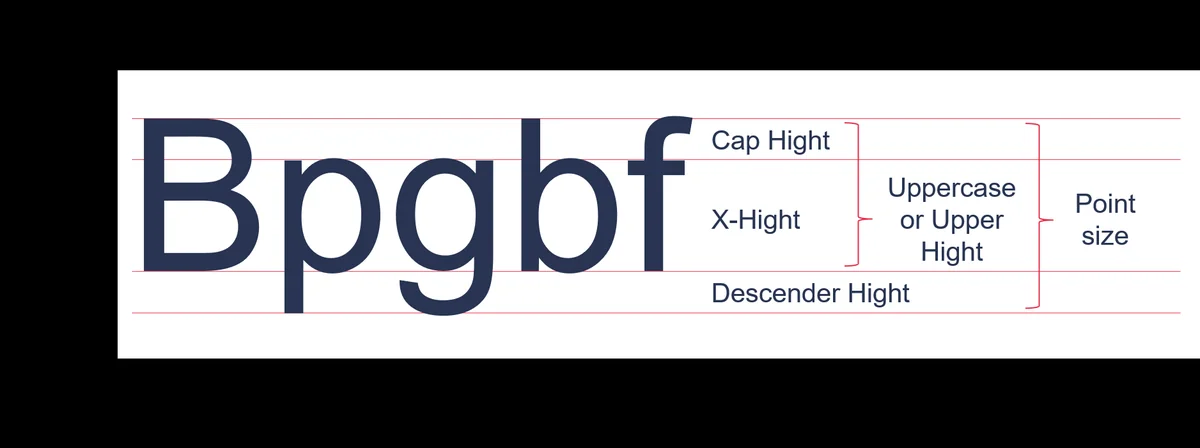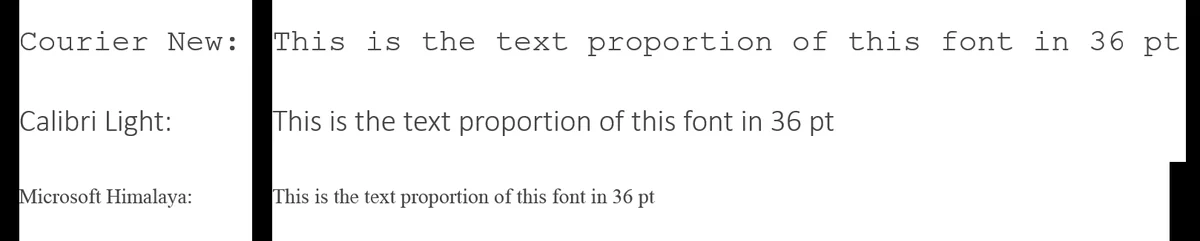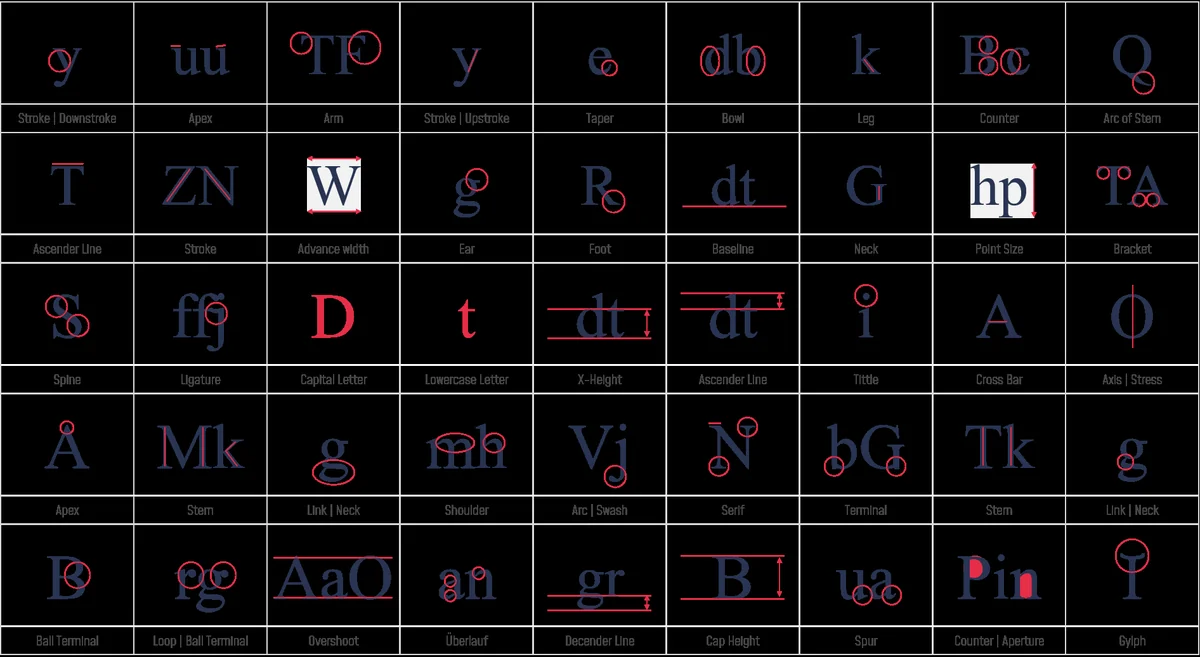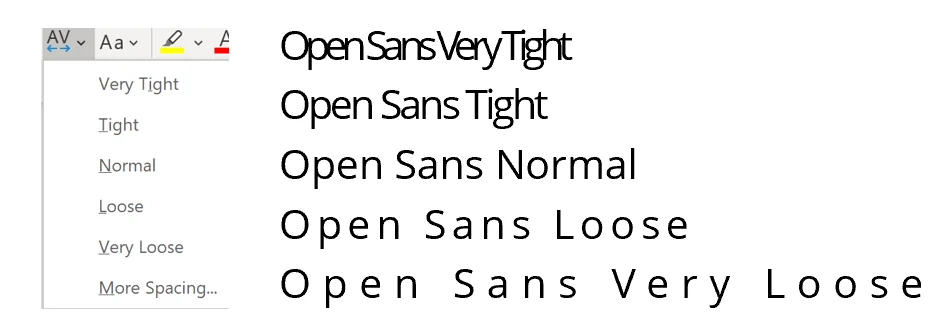
¿Te has fijado alguna vez en que, especialmente, los libros económicos, la literatura trivial, las novelas policiacas de bolsillo baratas e incluso los libros infantiles y juveniles se imprimen con fuentes con serifas?
Las fuentes limpias que presentan cierta simetría se denominan Antiqua lineales.
Arial, Calibri, Gill Sans y Futura son solo algunos ejemplos de Antiqua lineales sans serif. Sus características son la rectitud y el poco contraste entre sus diferentes grosores. Muy a menudo, la altura ascendente de las letras minúsculas es igual a la altura de las mayúsculas.
Ah, otra vez aparecen palabras de vocabulario: